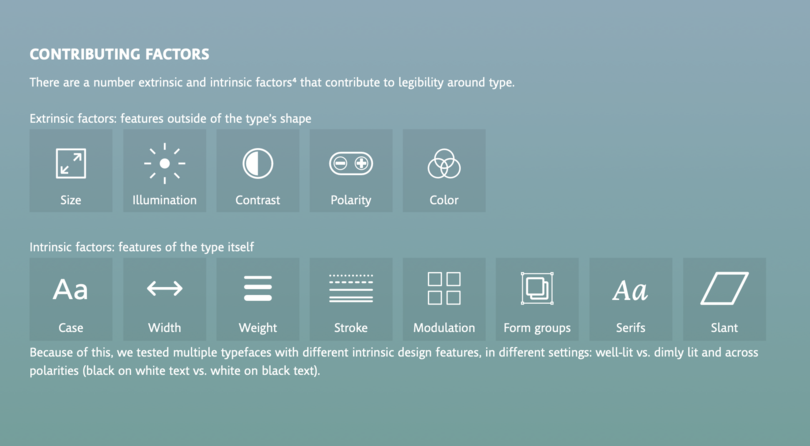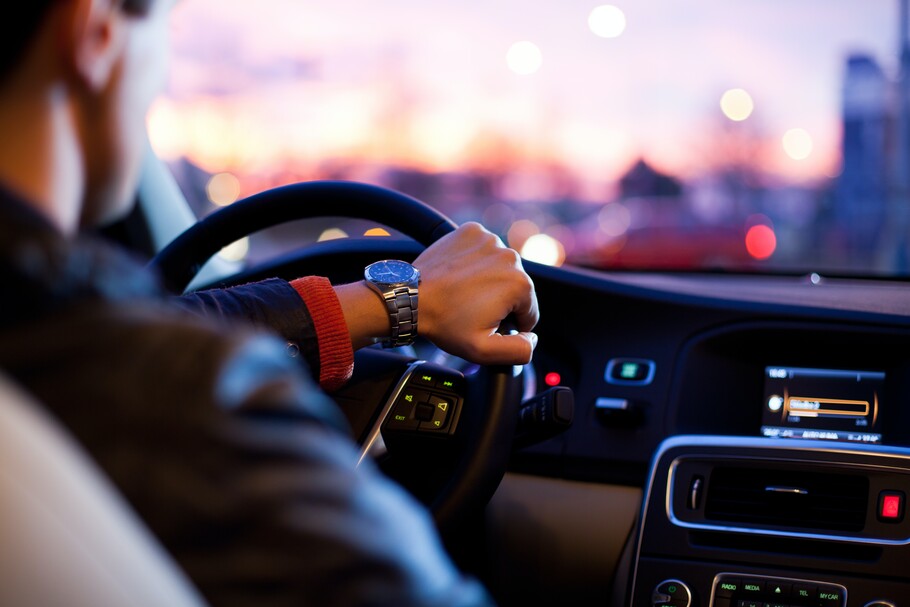
Sind futuristische Schriften wirklich zukunftstauglich?
Ich denke, uns Designern sollte klar sein, dass die Konzepte aus Science-Fiction-Filmen, die so fantasievoll und bahnbrechend aussehen, genauso wenig in der realen Welt funktionieren wie die Fahrzeuge in diesen Filmen.
A man is shown driving a car as if the viewer is in the back seat.
Warum sehen Technik und Design in Science-Fiction-Filmen immer ganz anders aus, als das, was im realen Leben wirklich kommt? Darüber sprach der Designer und Forscher Dave Addey mit Terrance Weinzierl, Creative Type Director bei Monotype und Moderator, in der jüngst erschienenen Folge unseres Creative Characters-Podcasts.
Als ein Beispiel führt Dave die transparenten Bildschirme in Minority Report (YouTube: Minority Report ‚s gesture-based user interface) und anderen Filmen an, die in der Vorstellung beeindruckend aussehen, in der Realität aber ein Alptraum für die Lesbarkeit wären.
„Uns Designern sollte klar sein“, betont Addey, „dass die Konzepte aus Science-Fiction-Filmen, die so fantasievoll und bahnbrechend aussehen, genauso wenig in der realen Welt funktionieren wie die Fahrzeuge in diesen Filmen.“
Einige der Schriften, die Filmemacher einsetzen um die Zukunft zu beschreiben, funktionieren im echten Leben nicht wirklich gut. Terrance und Dave erinnern sich an einige Sci-Fi-Schriften der 1970er und 1980er Jahre, darunter Eurostile von Aldo Novarese (2008 als Eurostile Next wiederveröffentlicht), die nach der Kinopremiere in der Autowerbung eingesetzt wurden. Ihr Aussehen war vom Zeitgeist und der Ästhetik des Automobils geprägt, aber nicht von Kriterien wie Lesbarkeit oder Lesekomfort.
Vor einigen Jahren arbeitete Monotype mit dem Massachusetts Institute of Technology (MIT) zusammen, um herauszufinden, ob Eurostile Next eine gute Wahl für Displays in Fahrzeugen sei. Die Studie untersuchte die Auswirkungen von Typografie und Schriftdesign auf die Lesbarkeit des Armaturenbretts. Indem wir ein Fahrsimulationsexperiment in einem Auto mit Eye-Tracking-Technologie einrichteten, konnten wir die Auswirkungen der Schriftwahl auf die Betrachtungszeit und die Reaktionszeit über mehrere Variablen hinweg untersuchen. Wir testeten eine Reihe von intrinsischen und extrinsischen Designfaktoren wie Farbe, Positiv-Negativ-Darstellung, Schriftart und -größe sowie die typografischen Eigenschaften von zwei verschiedenen Schriftarten: Frutiger und Eurostile
Nicht wirklich straßentauglich.
Mit den Tests konnten wir nachweisen, dass die Wahl einer Schrift mit bestimmten Merkmalen die Lesbarkeit eines Fahrzeug-HMI verbessern und dadurch die Betrachtungszeit der Fahrerinnen und Fahrer verringern kann. Frutiger, eine humanistische Schrift mit offenen Formen, großzügigen Zeichenabständen und unverwechselbaren Lettern, erwies sich als besser lesbar als die geometrische Grotesk Eurostile.
Manchmal sieht die Zukunft anders aus als vorhergesagt. Doch in diesem Fall geht es darum, die beste Technologie im Auto zu verwenden, um sicher auf der Straße zu fahren. Falls Sie mehr über die zitierte Studie zur Lesbarkeit erfahren möchten, lesen Sie den Artikel „The Art of the Glance“ (Die Kunst des Augenblicks) im Print-Magazin vom Sommer 2017 oder laden Sie unser eBook „How to win the in-car technology race“ (Gewinnen Sie das Rennen um die In-Car-Technologie) herunter.